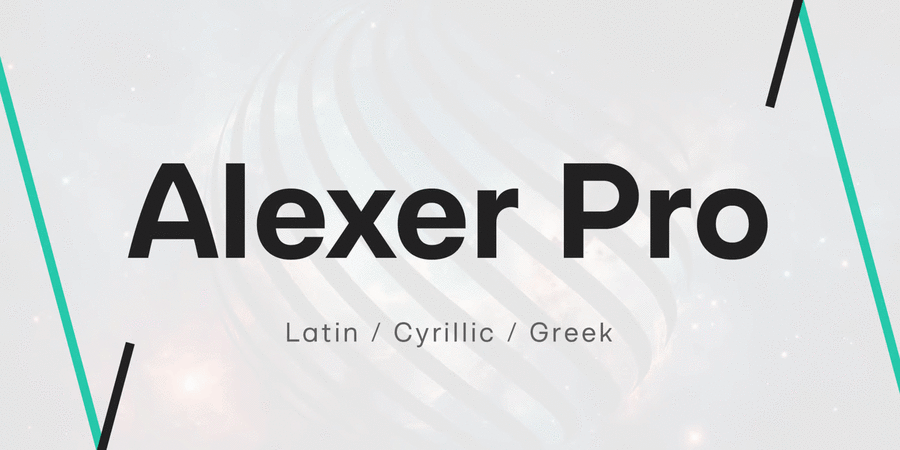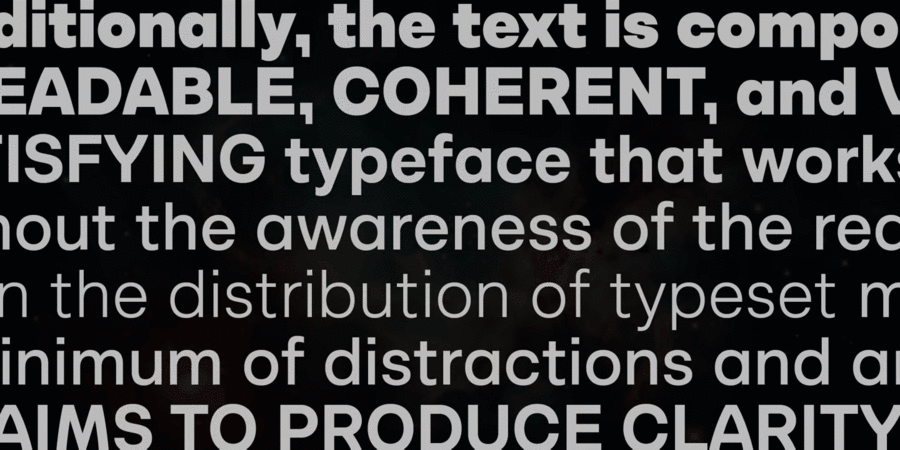
Alexer Pro — це сучасне сімейство шрифтів на основі гарніттури Alexer. Підтримка мов: латиниця (включно з в'єтнамською), кирилиця та грецька. Шрифт поставляється в 12 накресленнях, 6 насиченостях і 6 відповідних курсивах. Кожне накреслення включає 1300 гліфів, альтернативи (G, I, t) і функції OpenType. Це сімейство ідеально підходить для дизайну пакування, заголовків, реклами та фірмового стилю. Також підходить для вебдизайну, вивісок і редакційного дизайну.
Шрифт розробив Микола Савчук у 2022 році.
Асоціації з сімейством шрифтів Alexer ProОсобистість і характер гарнітури:
делікатний, чистий, легкий, прохолодний, свіжий, модний, міський, тонкий, сучасний, ясний, рівний, зрозумілий, якісний, точний, гнучкий, приємний, комфортний, зручний, інтимний, ніжний, технічний, гладенький, оригінальний, затишний, неоновий, статичний, мотивуючий, твердий, чіткий, сильний, серйозний, впевнений, стійкий, переконливий, важливий, помітний, яскравий, важкий, потужний, активний, наполегливий, суворий
парфумерія, лосьйон, краса, туалетна вода, шампунь, косметика, перукарня, дієта, дизайн, гігієна, чистота, інтер'єр, АСМР, Інстаграм, вода, здоров'я, екологія, Місто, небо, торгівля, аеропорт, автобус, меблі, кафе, ресторан, їжа, обід, метро, ліки, аптека, транспорт, шоу, телебачення, паливо, енергетика, електростанція, технології, Доставка, логістика Гарнітура має ознаки стилів: